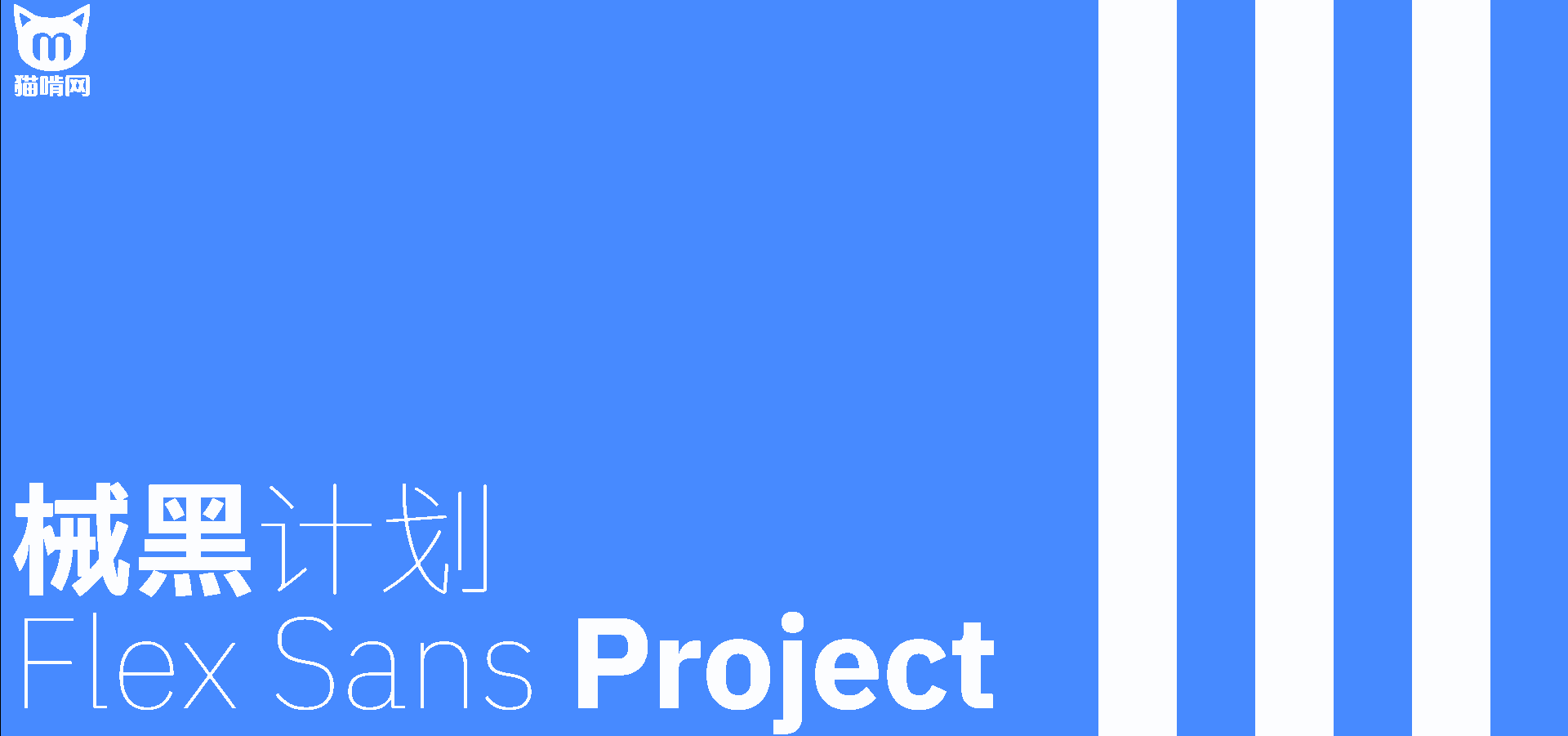
械黑 GB
械黑计划(Flex Sans Project)是一款基于 IBM Plex Sans 中文字体重新优化打造的免费可商用无衬线字体项目。项目以 IBM 于 2025 年公开发布的 Plex 字体源代码为基础,针对此前 IBM Plex Sans SC 在简体中文设计中的部分字形问题进行了系统修复,并新增可变字体支持,在延续 IBM Plex 系列鲜明设计语言的同时,进一步提升了中文排版品质与屏幕显示效果,适用于界面设计、品牌视觉、数字产品及现代出版等多种应用场景。
从整体字形来看,械黑计划继承了 IBM Plex 系列理性、现代、科技感十足的设计风格。字体结构规整紧凑,横竖比例协调,整体重心稳定,视觉节奏统一。与传统黑体相比,械黑更强调几何秩序与现代工业设计语言,在保证阅读效率的同时,也具有较高的品牌辨识度,非常适合作为 UI 界面、网页设计、软件系统、企业视觉及科技产品中的基础字体。
从笔画细节来看,字体完整保留了 IBM Plex 最具代表性的 Ink Trap(油墨陷阱) 设计特征。在笔画交汇、转角及狭窄区域加入精细的内凹处理,不仅延续了 Plex 家族独有的视觉个性,同时也有效提升了小字号及低分辨率屏幕下的显示清晰度。随着字号增大,这些细节又成为字体独特的设计语言,使整体既具有功能性,又富有现代工业美学特征。
在字形规范方面,械黑目前已完成 GB(国标)版本 的开发,在尽可能符合中国国家规范字形的基础上,保留 Plex JP 与 Plex TC 中具有代表性的油墨陷阱设计。项目同时规划推出 SC(简中)版本,将在保留 IBM Plex 原有印刷风格的同时,更贴近日常简体中文阅读与使用习惯,为不同设计需求提供更加灵活的选择。
作为可变字体(Variable Font)项目,械黑支持连续字重调节,可根据不同终端、屏幕尺寸及排版需求自由控制字体粗细,提高字体在数字产品、响应式网页、移动端应用及品牌系统中的适配能力,也进一步增强了整体排版效率。
械黑计划是在 IBM Plex 中文字体基础上的一次高质量优化与重构,既保留了 Plex 家族极具辨识度的油墨陷阱设计语言,又针对中文字形进行了更加符合本土阅读习惯的调整,并加入可变字体支持。无论是界面设计、品牌视觉、数字产品还是现代出版排版,都能够提供兼具美观性、可读性与专业性的免费开源字体解决方案。